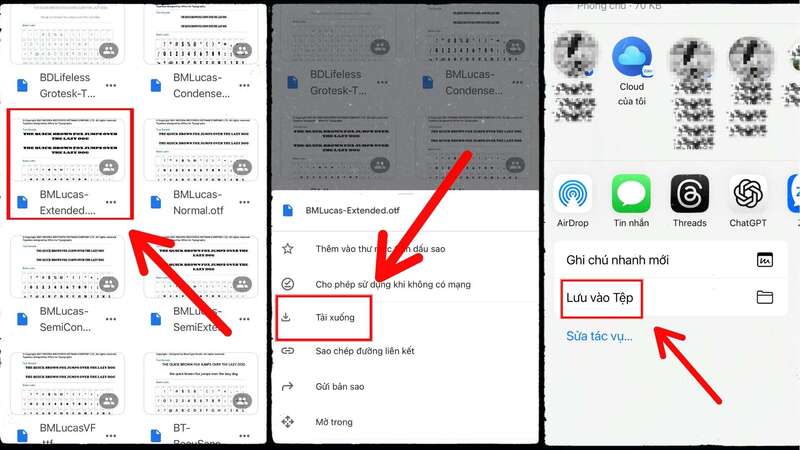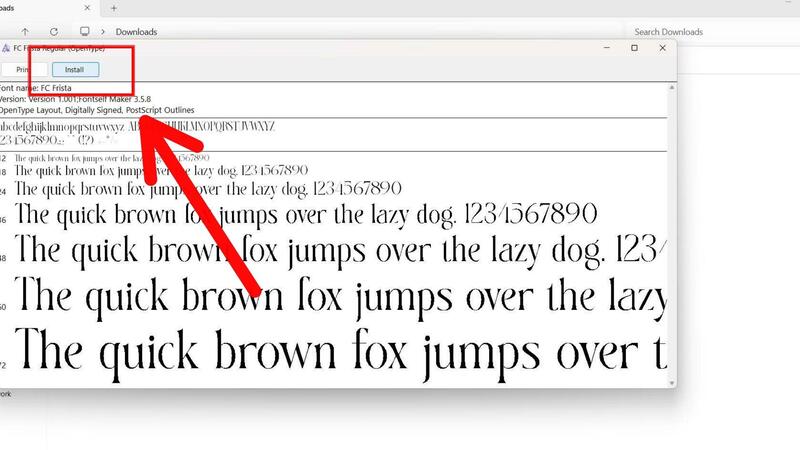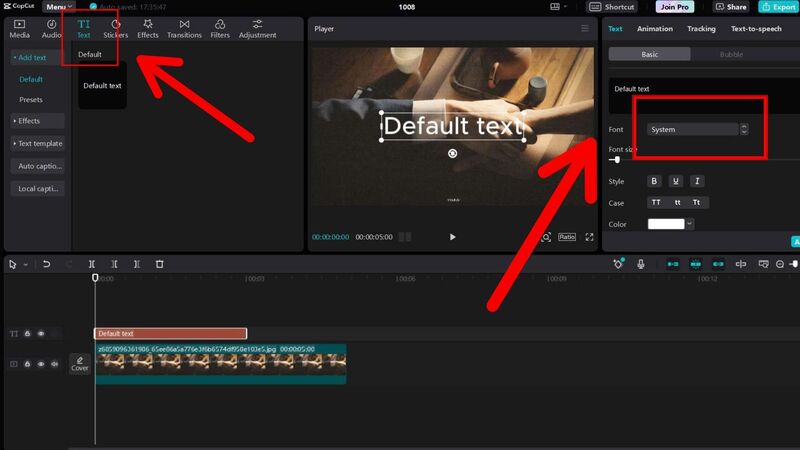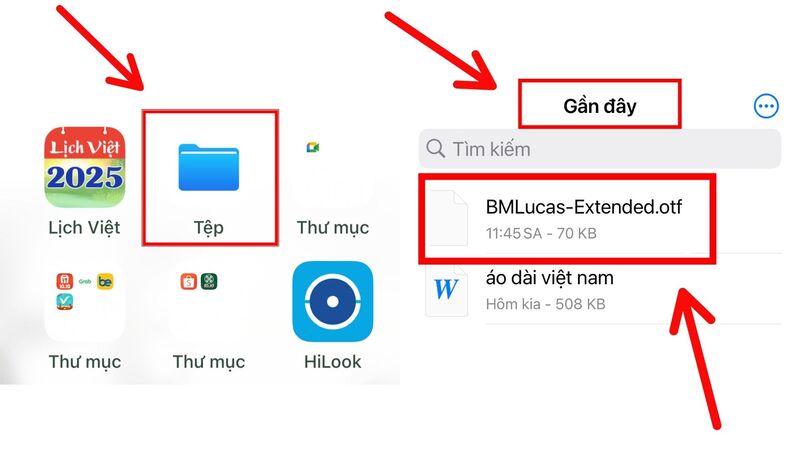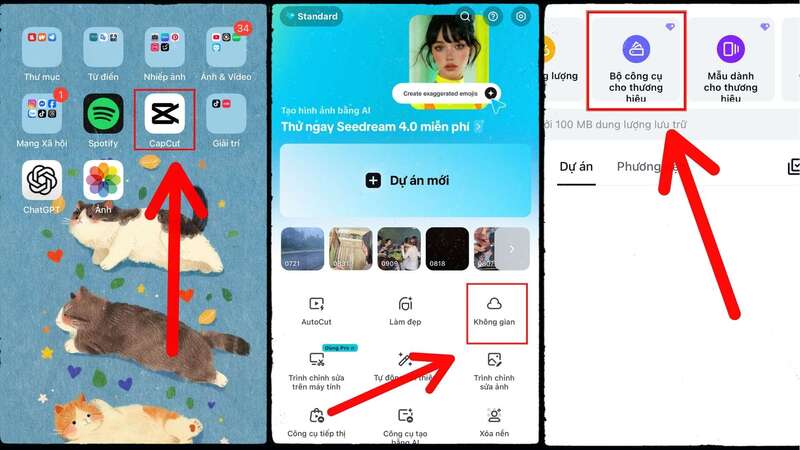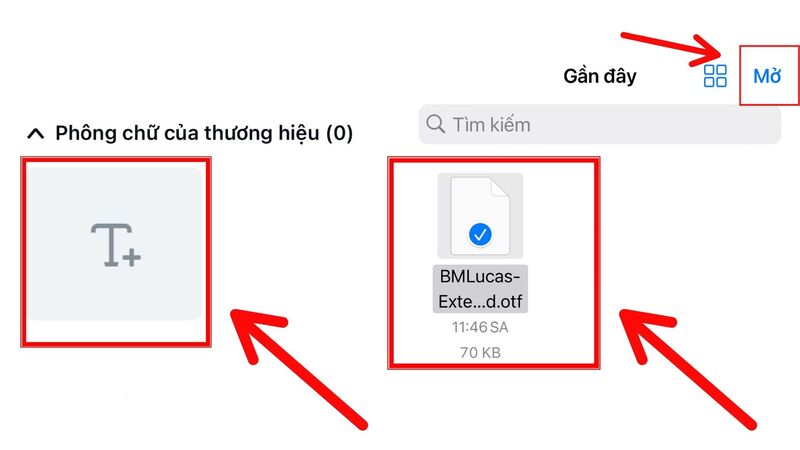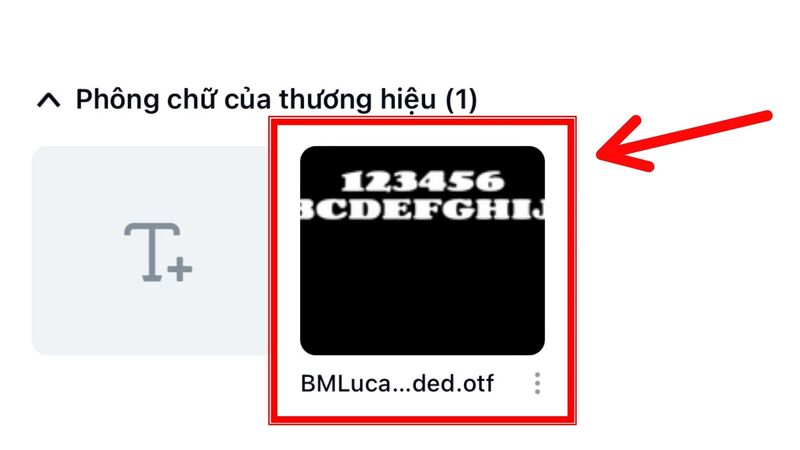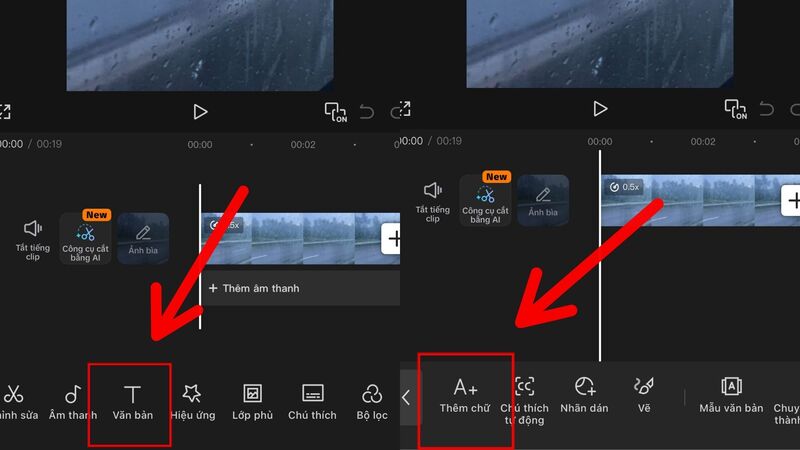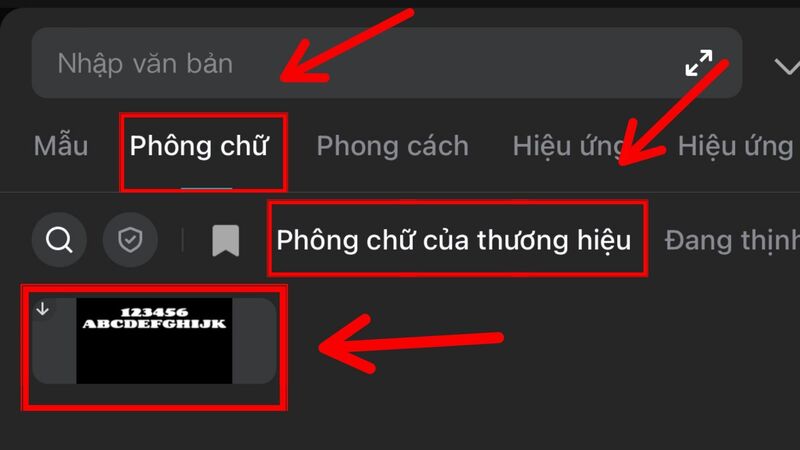
Việc thêm font chữ vào CapCut không chỉ tạo dấu ấn cá nhân mà còn tăng tính thẩm mỹ cho video. Dù dùng trên điện thoại hay máy tính, thao tác này giúp bạn định hình phong cách và làm nội dung nổi bật. Bài viết sau sẽ hướng dẫn chi tiết cách thêm font chữ vào CapCut và mẹo khắc phục lỗi thường gặp để bạn chỉnh sửa hiệu quả hơn.
Tìm hiểu cách thêm font chữ vào CapCut cho cả điện thoại và máy tính dễ dàng
Việc thêm font chữ không chỉ làm video đẹp hơn mà còn giúp thể hiện cá tính sáng tạo của người làm nội dung. Khi sử dụng cùng một kiểu chữ xuyên suốt, bạn sẽ dễ dàng tạo nên phong cách riêng hoặc hình ảnh thương hiệu nhất quán. Nhờ đó, người xem có thể nhanh chóng nhận ra video của bạn giữa hàng loạt nội dung khác.
Một video có bố cục, màu sắc và phông chữ đồng nhất luôn tạo cảm giác chuyên nghiệp hơn. Font chữ phù hợp sẽ giúp nội dung trở nên cân đối, bắt mắt và có điểm nhấn. Sự chỉn chu này thể hiện sự đầu tư nghiêm túc, khiến người xem tin tưởng và đánh giá cao chất lượng sản phẩm.
Ngoài yếu tố thẩm mỹ, font chữ còn ảnh hưởng trực tiếp đến cách người xem tiếp nhận thông tin. Khi chữ dễ đọc, rõ ràng và trình bày hợp lý, thông điệp trong video sẽ được truyền tải nhanh hơn và hiệu quả hơn. Kết hợp với các hiệu ứng chuyển động mềm mại, video của bạn sẽ trở nên sinh động và thu hút hơn rất nhiều.
Bổ sung thêm nhiều font chữ giúp bạn có thêm “chất liệu” để sáng tạo. Mỗi kiểu chữ mang đến một sắc thái khác nhau, phù hợp cho từng chủ đề video. Nhờ đó, bạn có thể thử nghiệm nhiều phong cách, giúp nội dung luôn tươi mới và mang đậm dấu ấn cá nhân.
Thêm font chữ vào CapCut để mở rộng khả năng sáng tạo nội dung
Nếu chữ bị mất dấu hoặc hiển thị không đúng định dạng, rất có thể font bạn dùng không hỗ trợ tiếng Việt hoặc file bị lỗi. Khi gặp tình huống này, hãy chọn lại một font có hỗ trợ tiếng Việt và thử cài đặt lại để phần mềm nhận diện đúng định dạng chữ.
Không phải font nào cũng phù hợp cho video. Một số kiểu chữ nghệ thuật tuy nổi bật nhưng dễ gây rối mắt, đặc biệt khi chèn nội dung nhiều chữ. Trong trường hợp này, bạn nên chọn những font đơn giản, rõ nét, dễ đọc để giúp tổng thể video cân đối và chuyên nghiệp hơn.
Qua hướng dẫn chi tiết trên, hy vọng bạn đã biết cách thêm font chữ vào CapCut trên cả điện thoại và máy tính để tạo phong cách riêng cho video. Khi sử dụng đúng font, nội dung sẽ trở nên sinh động, rõ nét và chuyên nghiệp hơn.